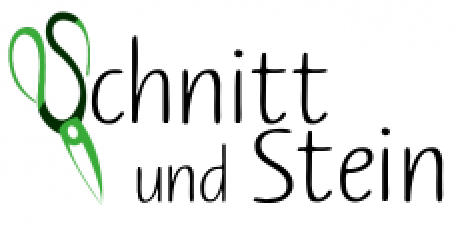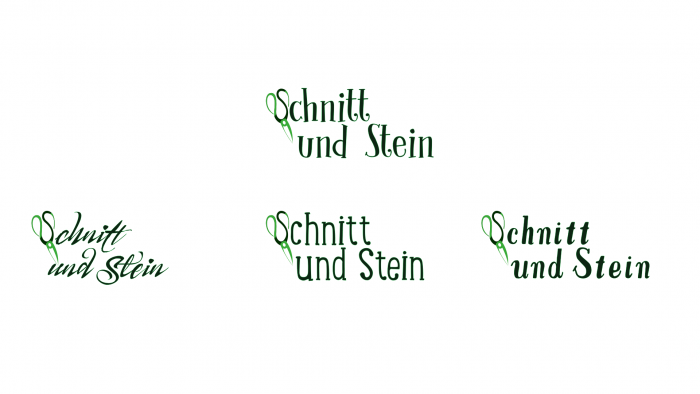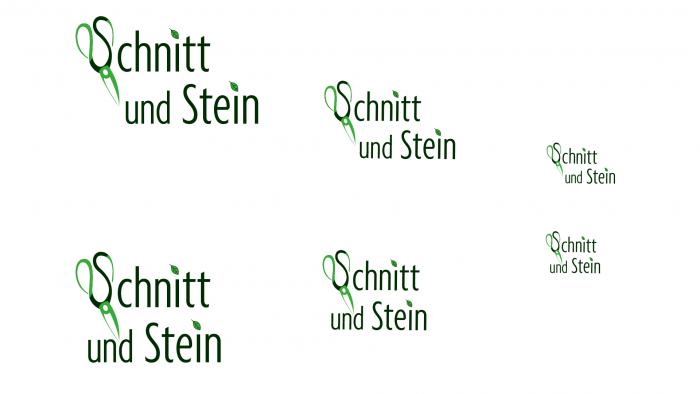
Hilfe bei Logoentwicklung
@Schnitzel, ok, ich werde mich nach einer organischeren Schrift umschauen und die Schere anpassen!!
Die grundsätzliche Positionierung der Schere ist jetzt mE sehr gut, so kommt die (pfiffige!) Startidee gut raus!
Mir gefällt der letzte Entwurf eigentlich schon richtig gut. Ich würde höchstens die S-Schere einen Haucgh nach unten setzen, denn da die Klingen der Schere das dunklere S ein wenig anknabbern, wirkt das S, als währe es ein wenig höher gerutscht - bestimmt eine optische Täuschung, aber damit wird in der Typografie ja andauernd gespielt.
@Kathrinvdm
@BerndH
@catfonts
Du hast recht, die S-Schere muss einen Tick nach unten, jetzt sehe ich es auch!
An alle:
Anbei dann doch noch ein paar andere Schriften, die etwas verspielter sind oder organischer --
wie man es sehen will. Ich habe eine "hausinterne Umfrage" bei mir zu Hause gemacht und
die vier Kandidaten sind übrig geblieben ...
Gregor
p.s: Es handelt sich hier nur um eine Pixel-Collage, da ist noch nix ausgemittelt und so...
Du kommst gut voran, das wird was.
Einen Gedanken habe ich noch, aber ich muss mir erst einen Asbest-Anzug holen, da er der reinen Lehre widerspricht.
So, jetzt:
Obwohl eigentlich das Ampersand ja nur dazu dienen soll, in Firmennamen die Firmeninhaber (und nicht etwa Tätigkeiten) zu verbinden, könnte ich mir vorstellen, dass es hier mit Gewinn in die Gestaltung einfließen kann, und zwar m.E. eher die kursive als die gerade Form. Vielleicht grob in die Richtung des fünften in der ersten Zeile der Grafik hier, etwas runterscrollen, natürlich einfacher.
Ich kann mir nicht helfen – die sind mir alle zu verspielt und würden prima zu Fantasy-Romanen passen. Aber zu Gartenbau?
Aber es kommt natürlich drauf an, wie die Firma deines Bekannten ausgerichtet ist. Vielleicht macht er ja verwunschene Märchengärten …
Ich glaube ein Ampersand, besonders noch ein verspieltes wie in Bernds Beispiel stiehlt der Schere die Show. Das wären dann 2 Hingucker auf einmal.
Ich denke, in Logos darf man – wie mit vielen Regeln – auch mit dem Ampersand etwas großzügiger umgehen. Ich selber verwende es auch, um bei meinem Logo Design & Illustration zu verbinden. Der Vorteil in meinem Fall ist, dass das so relativ sprachneutral ist, zumindest, was den deutsch- und englischsprachigen Raum angeht.
Bei Gregors Logo dürfte es jedoch schwierig werden mit dem Ampersand, weil es sich – je nach verwendeter Form – mit der Schere beißen könnte. Ich würde es aber auf jeden Fall mal ausprobieren – schon weil ich die Vorstellung, es könnten vielleicht doch Frau Schnitt und Herr Stein dahinterstecken, sehr charmant finde. Sollte es nicht klappen mit dem Ampersand, dann würde ich bei einigen der Entwürfe den Leerraum zwischen »und« und »Stein« etwas verkleinern, speziell bei den mittleren beiden Entwürfen, da klafft eine störende Lücke.
Was die Schriftarten angeht, da stimme ich Andrea zu – da kommt es sehr auf das Konzept an.
Ich glaube ein Ampersand, besonders noch ein verspieltes wie in Bernds Beispiel stiehlt der Schere die Show. Das wären dann 2 Hingucker auf einmal.
OK, kann ich gut verstehen - mir ging es nur um die kursive Grundform des &, die konkrete Gestaltung (ich schrieb etwas knapp: natürlich einfacher) sollte es ausdrücklich nicht zu einem Hingucker machen.
Die kursive Form hatte ich angeregt, weil die aufrechte in an dieser Stelle in unvorteilhafter Weise die S-Kurven der Schere aufgreifen würde und von ihr ablenkte.
Was die Schriftarten betrifft, eine eher romantische als technische Note ist natürlich durch die Nutzung dieser spezifischen Scherenform bereits gewählt; wenn ich an den eher unglücklichen Entwurf mit Steinumriss und Schnörkel zurückdenke, wohl auch vom Auftraggeber gewollt.
Ich glaube ein Ampersand, besonders noch ein verspieltes wie in Bernds Beispiel stiehlt der Schere die Show. Das wären dann 2 Hingucker auf einmal.
Bei Gregors Logo könnte es jedoch schwierig werden mit dem Ampersand, weil es sich – je nach verwendeter Form – mit der Schere beißen könnte. Ich würde es aber auf jeden Fall mal ausprobieren – schon weil ich die Vorstellung, es könnten vielleicht doch Frau Schnitt und Herr Stein dahinterstecken, sehr charmant finde.
... vielleicht könnte man aus dem Ampersand eine Schere machen?  :-?
Mich stört echt bei allen Entwürfen das vermurkste S – zumal es darunter nochmal in ›echt‹ vorkommt ...
Um dem Ampersand zur Seite zu springen etwas renommierte Fachliteratur:
Es darf laut Duden nur in Firmennamen benutzt werden (aber laut uns auch sonst, wo es Spaß macht) ...
Detailtypografie, Friedrich Forssmann/Ralf de Jong, Verlag Hermann Schmidt, Mainz, 2. Auflage, 2004
Ich würde trotzdem versuchen den Strichkontrast aus dem Scheren-S zu nehmen und damit die Schere noch geometrischer und einfacher zu gestalten, damit Schrift und Schere harmonischer wird. Ansonsten finde ich das Untere in seiner Kompaktheit schon ganz gut ...
Das Kurzenberger-Logo finde ich formal ja auch recht harmonisch, eigenartig finde ich nur, dass sie im Logo eine kaputte Brille anbieten. Ich, als Vater und Brillenkäufer für zwei arg weitsichtige Kinder, zucke da zusammen und denke: »Ach du Schande, das wird wieder teuer ..!«